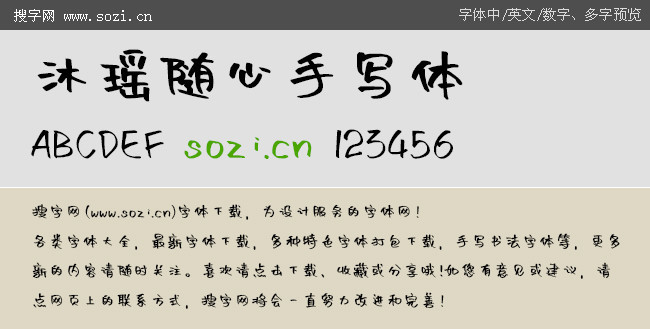
沐瑤隨心手寫(xiě)體
搜字網(wǎng)提供一款免費(fèi)可商用的沐瑤隨心手寫(xiě)體中文字體下載,沐瑤隨心手寫(xiě)體是一款由網(wǎng)名春顏秋色的設(shè)計(jì)師以女兒名字命名的第二款手寫(xiě)字體,并提供給大家免費(fèi)商用。這款字體休閑可愛(ài),適合兒童包裝設(shè)計(jì),網(wǎng)頁(yè)設(shè)計(jì),海報(bào)設(shè)計(jì)等場(chǎng)合使用。